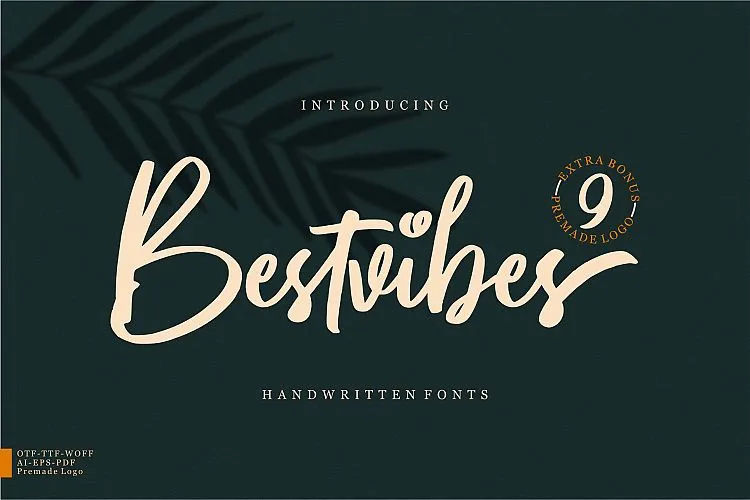
A fonte ‘Bestvibes Script Font’ é uma opção única para designers que buscam dar um toque autêntico às suas criações digitais. Ela traz à tona a ideia de escrever de maneira natural, permitindo aos designers criarem designs com muito potencial e originalidade. As diferentes estilos da fonte permitem uma grande variedade de opções para o design de inscrição em logotipos, convites, material de decoração, embalagens de produtos, postagens nas redes sociais, anúncios, etiquetas, fotos e até mesmo marcas especiais. Ideal tanto para designers profissionais quanto para iniciantes, a ‘Bestvibes Script Font’ oferece uma ampla variedade de letras maiusculas e minúsculas, números e sinais gráficos. Sem dúvidos, é uma excelente escolha para aqueles que buscam adicionar um toque único e autêntico às suas criações digitais.